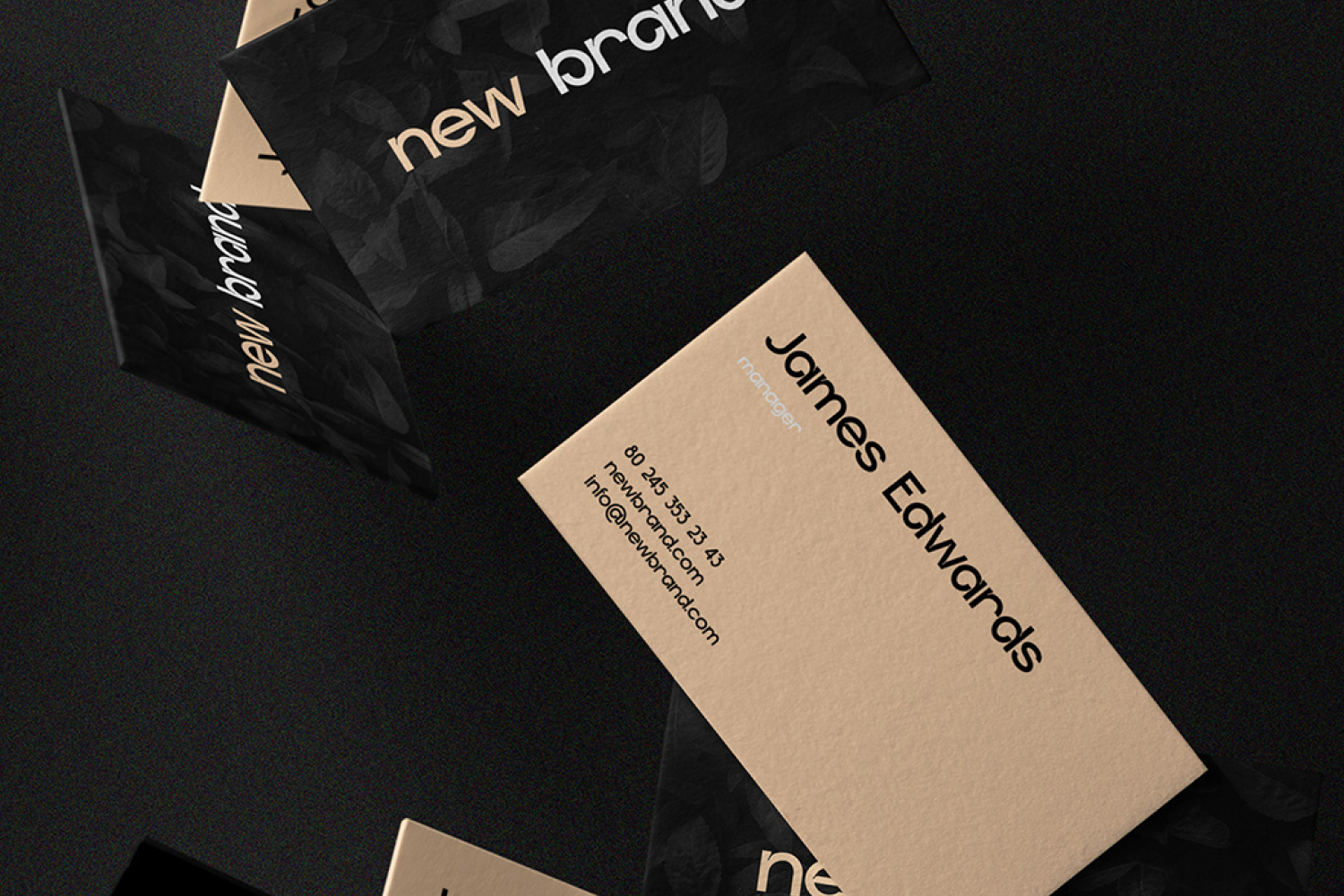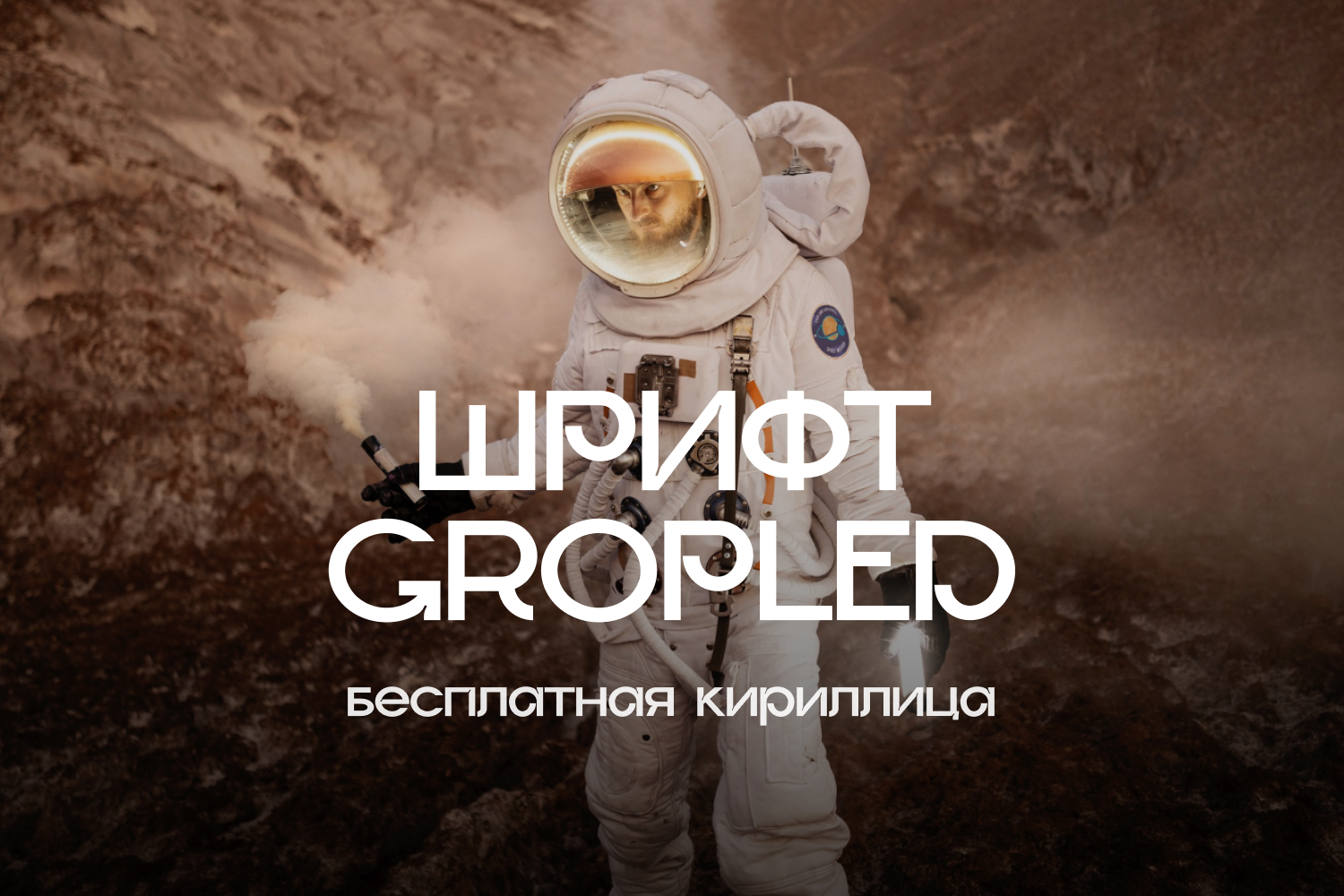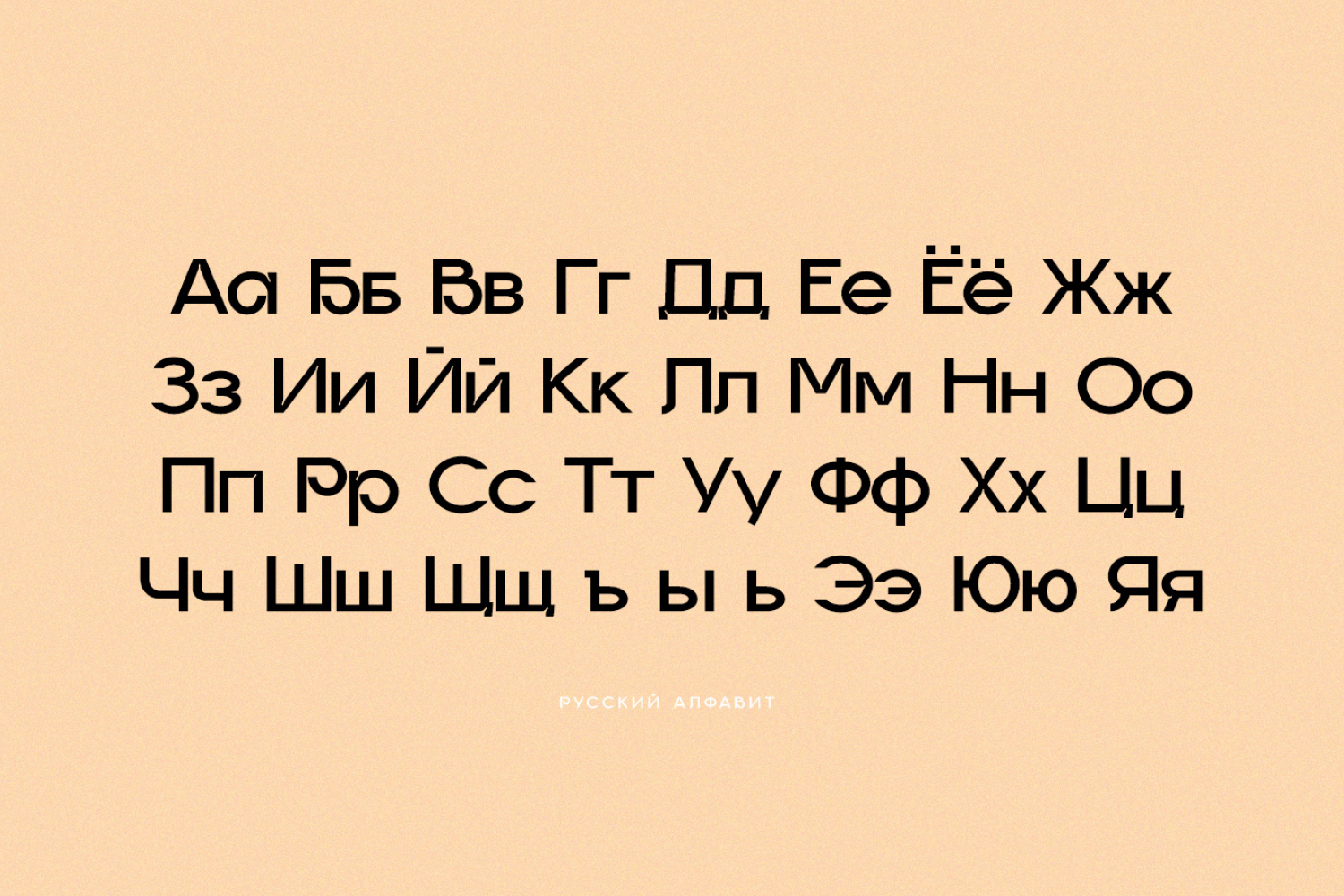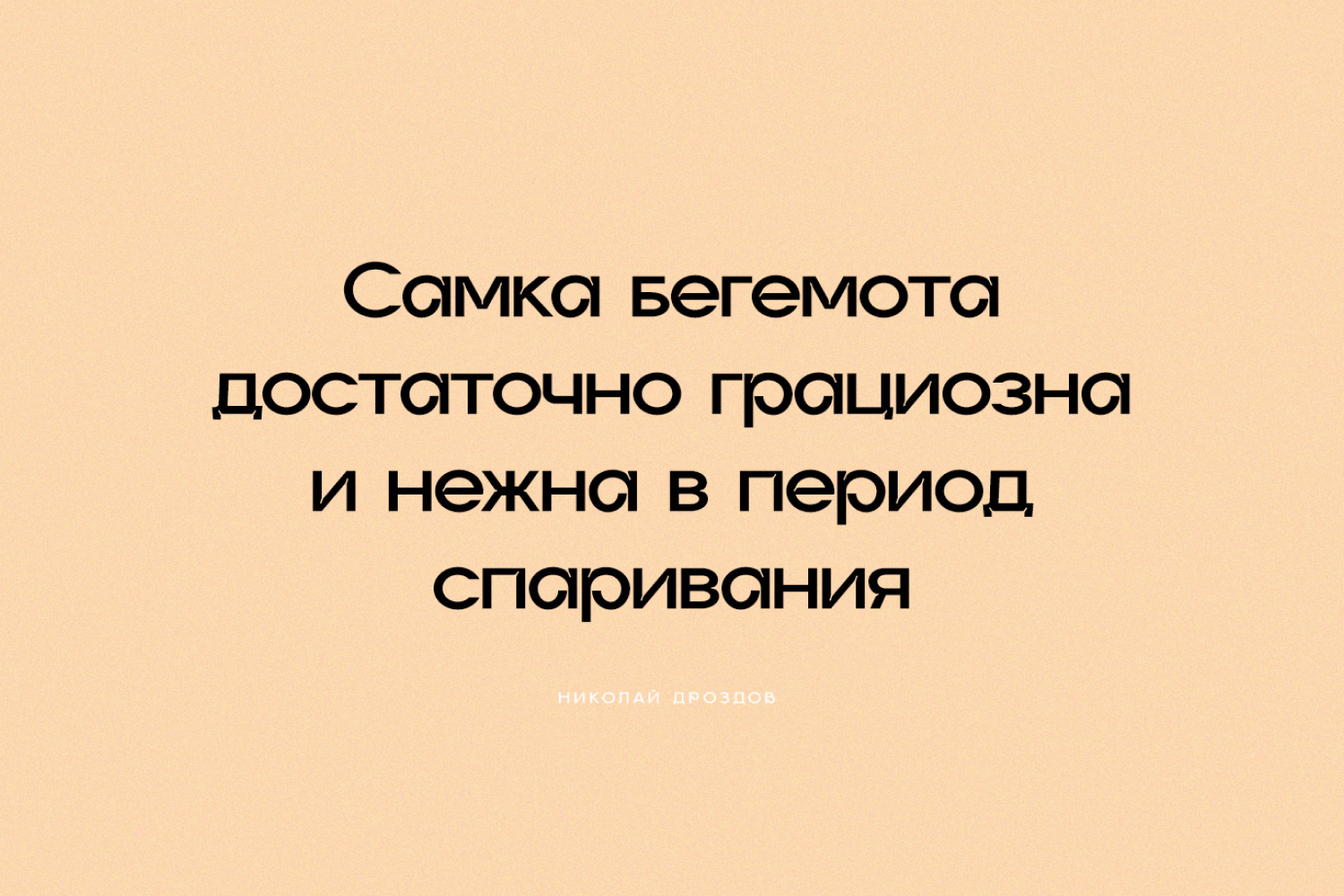
Шрифт gropled. Кириллица
Gropled отлично подходит для создания логотипов, типографики для веб-дизайна, дизайна плакатов и многого другого! Почти всю презентацию сохранил от автора.